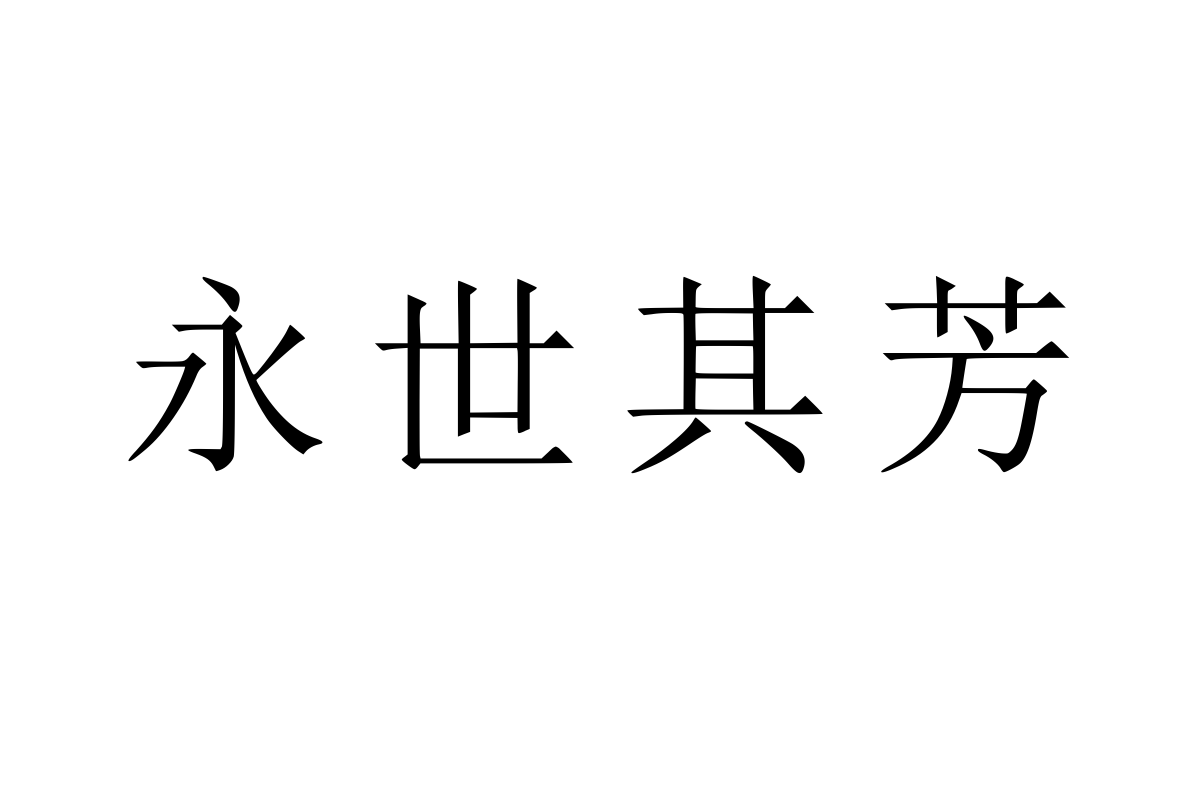
兰米宋韵字体是一款具有中国传统韵味的书法字体,它融合了现代审美和传统书法的元素,创造出独特的艺术风格。这种字体的特点主要体现在以下几个方面:
1. 字形优美:兰米宋韵字体的字形线条流畅,结构严谨,具有很强的视觉冲击力。它的笔画粗细适中,既有力度又有柔美,给人一种优雅的感觉。
2. 笔触自然:这种字体的笔画线条自然流畅,没有过多的装饰,给人一种朴实无华的感觉。它的笔触仿佛是在纸上随意挥洒,但又不失规矩,展现了一种独特的艺术魅力。
3. 结构严谨:兰米宋韵字体的结构严谨,每个字的笔画都经过精心设计,使得整体看起来既和谐又统一。这种结构使得字体在视觉上呈现出一种平衡感,给人以美感。
4. 易于识别:兰米宋韵字体的字形简洁明了,易于识别,适合用于各种印刷品和设计作品。它的线条流畅,结构严谨,给人一种强烈的视觉冲击力,使得读者能够迅速记住这个字体。
总的来说,兰米宋韵字体是一种具有中国传统韵味的书法字体,它融合了现代审美和传统书法的元素,创造出独特的艺术风格。这种字体的特点是字形优美、笔触自然、结构严谨和易于识别,使其在各种设计作品中得到了广泛的应用。